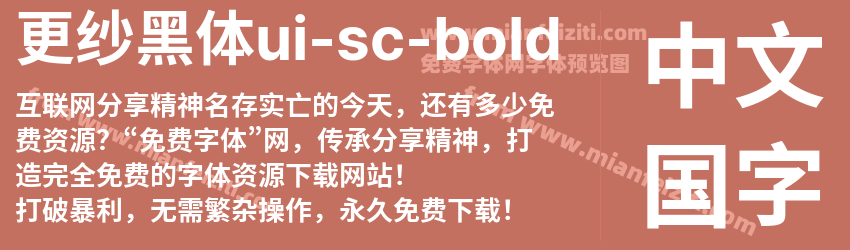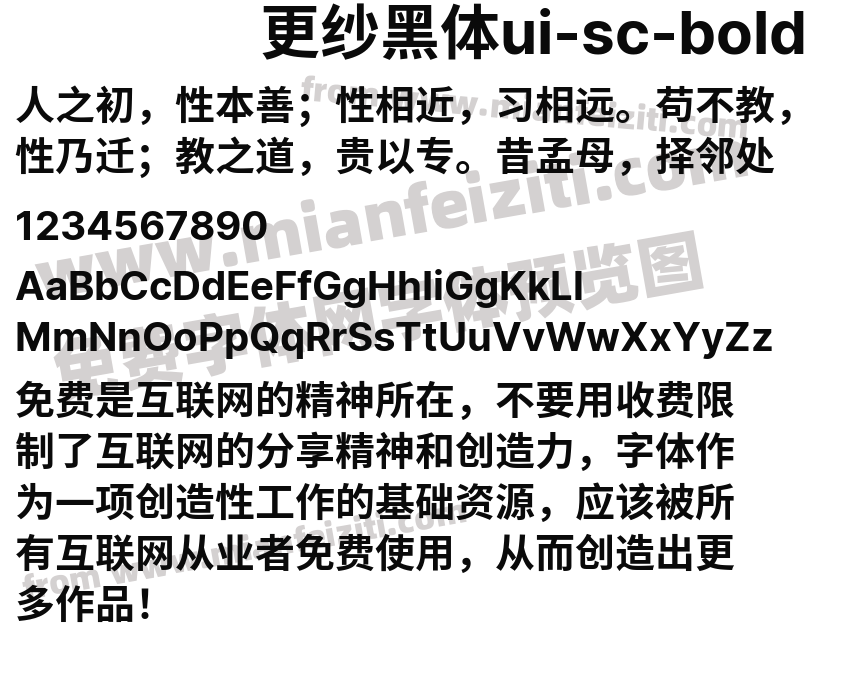
更纱黑体ui-sc-bold
字体名称: 更纱黑体ui-sc-bold
Postscript名称: Sarasa-UI-SC-Bold
更纱黑体ui-sc-bold预览图1
更纱黑体ui-sc-bold预览图2
更纱黑体ui-sc-bold字体映射图
本款“更纱黑体ui-sc-bold”是一款书写很新颖的字体,字体大方,适合各种设计作品使用!欢迎下载!